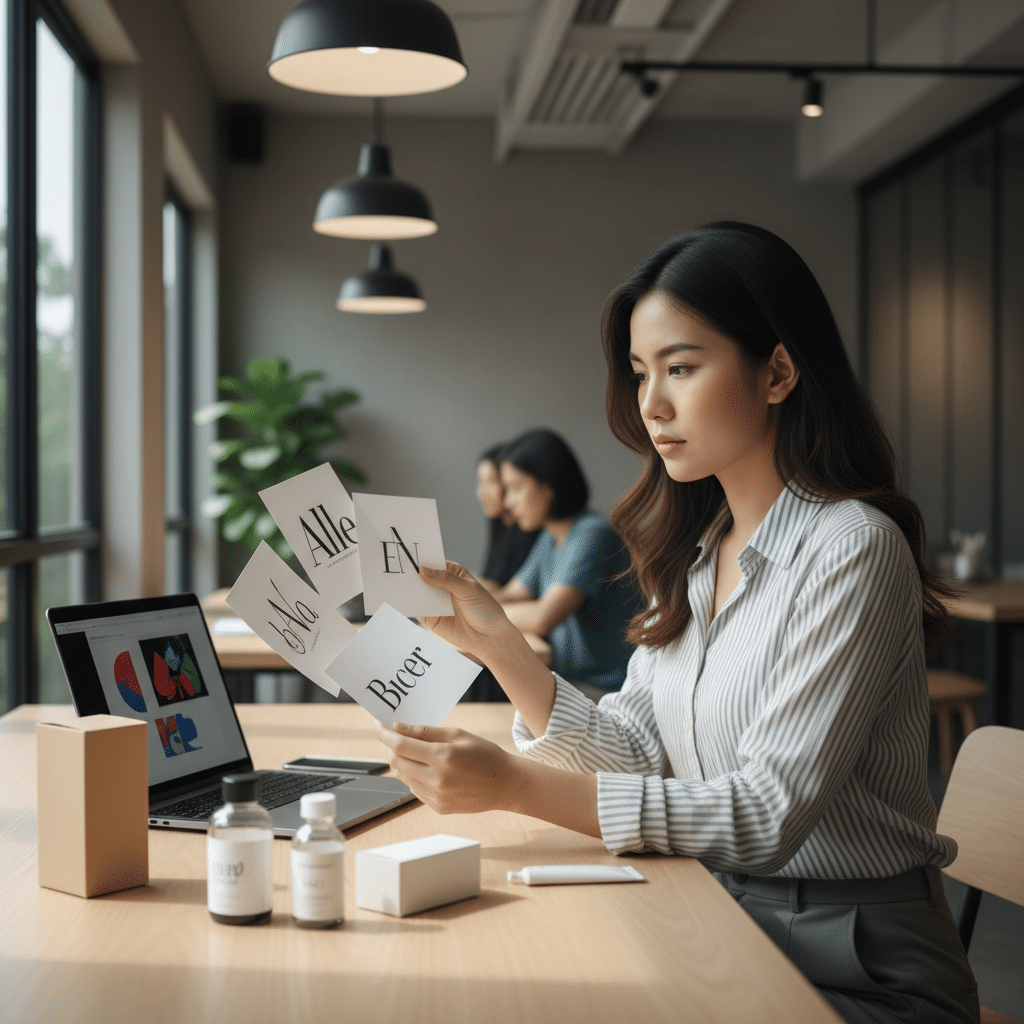
เลือกฟอนต์ผิด ชีวิตเปลี่ยน! จิตวิทยาฟอนต์สร้างแบรนด์ SME
การตัดสินใจว่า เลือกฟอนต์ผิด ชีวิตเปลี่ยน! จิตวิทยาฟอนต์สร้างแบรนด์ SME อาจฟังดูเกินจริง แต่ในความเป็นจริงแล้ว การเลือกใช้ตัวอักษรหรือฟอนต์ (Font) เป็นมากกว่าแค่การตัดสินใจด้านการออกแบบ เพราะมันคือเครื่องมือสื่อสารทรงพลังที่ส่งผลโดยตรงต่อการรับรู้และความน่าเชื่อถือของแบรนด์ในสายตาผู้บริโภค การเลือกฟอนต์ที่ไม่เหมาะสมอาจบ่อนทำลายความไว้วางใจและสร้างความเสียหายต่อความภักดีของลูกค้า ทำให้การตัดสินใจที่ดูเหมือนเล็กน้อยนี้กลายเป็นปัจจัยเชิงกลยุทธ์ที่สำคัญอย่างยิ่งต่อความสำเร็จของแบรนด์
สรุปประเด็นสำคัญของการเลือกใช้ฟอนต์
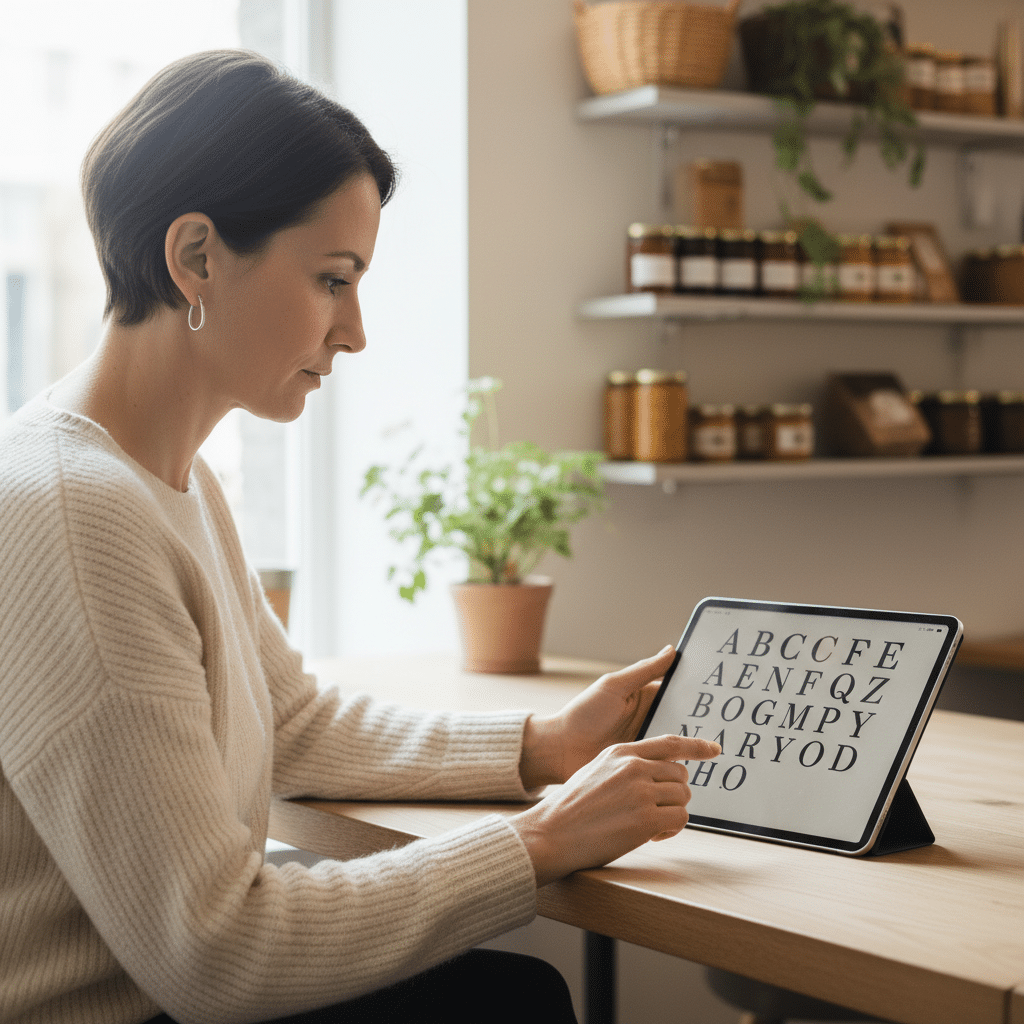
- การเลือกฟอนต์ส่งผลโดยตรงต่อการรับรู้: ฟอนต์ที่เหมาะสมสามารถเพิ่มการรับรู้ด้านนวัตกรรมได้ถึง 9% และสร้างความโดดเด่นให้แบรนด์ได้ 7%
- ฟอนต์สร้างความน่าเชื่อถือ: ฟอนต์ในกลุ่ม Geometric Sans-serif เช่น Gilroy Bold สามารถเพิ่มการรับรู้ถึงความน่าเชื่อถือและความเป็นของแท้ (Authenticity) ของแบรนด์ได้ถึง 5%
- ประเภทฟอนต์สื่อสารบุคลิกที่แตกต่าง: ฟอนต์กลุ่ม Serif (มีเชิง) สื่อถึงคุณภาพ ความหรูหรา และความน่าจดจำ ในขณะที่ฟอนต์กลุ่ม Sans-serif (ไม่มีเชิง) สื่อถึงความสำเร็จ ความจริงใจ และความทันสมัย
- ฟอนต์คืออัตลักษณ์ของแบรนด์: การเลือกฟอนต์เปรียบเสมือนการเลือกเครื่องแต่งกายให้กับแบรนด์ เป็นองค์ประกอบพื้นฐานที่กำหนดทิศทางการรับรู้ทั้งหมดของลูกค้าที่มีต่อแบรนด์
- ความผิดพลาดมีราคาสูง: สินค้าคุณภาพสูงที่ใช้ฟอนต์ไม่เหมาะสมอาจถูกมองว่าไม่น่าเชื่อถือ ในขณะที่แบรนด์สมัยใหม่ที่ใช้ฟอนต์ไม่เข้ากันอาจดูตกยุค ซึ่งส่งผลกระทบต่อยอดขายโดยตรง
จิตวิทยาฟอนต์คืออะไร และสำคัญต่อ SME อย่างไร
จิตวิทยาฟอนต์ (Font Psychology) คือการศึกษาว่ารูปแบบตัวอักษรที่แตกต่างกันส่งผลต่อความคิด ความรู้สึก และพฤติกรรมของมนุษย์อย่างไร ในบริบทของการสร้างแบรนด์สำหรับธุรกิจขนาดกลางและขนาดย่อม (SME) เรื่องนี้มีความสำคัญอย่างยิ่ง เพราะฟอนต์คือองค์ประกอบแรกๆ ที่ลูกค้าสัมผัสผ่านโลโก้ บรรจุภัณฑ์ เว็บไซต์ หรือสื่อส่งเสริมการขายต่างๆ มันทำหน้าที่เป็น “ภาษากาย” ของแบรนด์ สื่อสารบุคลิกภาพและคุณค่าออกไปก่อนที่ลูกค้าจะได้อ่านข้อความเสียอีก
สำหรับเจ้าของธุรกิจ SME ที่มีทรัพยากรจำกัด การทำความเข้าใจในเรื่องนี้ถือเป็นความได้เปรียบในการแข่งขัน การเลือกฟอนต์ที่ถูกต้องตั้งแต่เริ่มต้นสามารถสร้างความไว้วางใจ สร้างความแตกต่างจากคู่แข่ง และดึงดูดกลุ่มเป้าหมายที่ใช่ได้โดยไม่ต้องใช้งบประมาณมหาศาล ในทางกลับกัน การมองข้ามความสำคัญของฟอนต์อาจทำให้การลงทุนด้านการตลาดอื่นๆ ไม่เกิดประสิทธิภาพเท่าที่ควร เพราะภาพลักษณ์ของแบรนด์ขาดความน่าเชื่อถือหรือไม่สอดคล้องกัน
พลังของฟอนต์ที่ส่งผลต่อการรับรู้แบรนด์
พลังของตัวอักษรนั้นมีผลกระทบที่สามารถวัดผลได้ต่อการที่ผู้บริโภคจะมองแบรนด์ของคุณอย่างไร ฟอนต์ที่ปรากฏบนโลโก้ ฉลากสินค้า หรือสื่อการตลาดต่างๆ เป็นตัวกำหนดการรับรู้ของลูกค้าในหลายมิติ ตั้งแต่ความน่าเชื่อถือไปจนถึงความทันสมัย
สร้างความน่าเชื่อถือและความโดดเด่น
ลองจินตนาการถึงธนาคารหรือสถาบันการเงินที่ใช้ฟอนต์ลายมือแบบเด็กๆ บนหน้าเว็บไซต์ หรือแบรนด์สินค้าแฟชั่นสุดหรูที่ใช้ฟอนต์หนาเทอะทะบนป้ายราคา ความรู้สึกขัดแย้งที่เกิดขึ้นนี้สามารถทำลายความไว้วางใจของลูกค้าได้ในทันที สินค้าที่มีคุณภาพยอดเยี่ยมอาจถูกมองว่าไม่น่าเชื่อถือหากจับคู่กับฟอนต์ที่ดูราคาถูกหรือไม่เป็นมืออาชีพ ในขณะเดียวกัน แบรนด์ที่ต้องการสื่อสารถึงความทันสมัยและนวัตกรรมอาจดูตกยุคไปถนัดตาหากเลือกใช้ฟอนต์ที่ไม่สอดคล้องกัน สิ่งเหล่านี้ส่งผลโดยตรงต่อการตัดสินใจซื้อและความภักดีของลูกค้าในระยะยาว
ตัวอย่างผลกระทบจากงานวิจัย
ข้อมูลจากการวิจัยแสดงให้เห็นถึงผลกระทบที่เป็นรูปธรรมของการเลือกใช้ฟอนต์:
- การรับรู้ด้านนวัตกรรม (Perceived Innovation): การเลือกฟอนต์ที่เหมาะสมสามารถเพิ่มการรับรู้ว่าแบรนด์มีความเป็นนวัตกรรมได้ถึง 9%
- ความโดดเด่นของแบรนด์ (Brand Distinctiveness): ฟอนต์ที่ใช่ช่วยเสริมสร้างความแตกต่างและทำให้แบรนด์โดดเด่นจากคู่แข่งได้มากขึ้น 7%
- ความน่าเชื่อถือและความเป็นของแท้ (Authenticity): ฟอนต์ประเภท Geometric Sans-serif ที่ได้รับความนิยมทั่วโลกอย่าง Gilroy Bold ได้รับการพิสูจน์แล้วว่าสามารถเพิ่มการรับรู้ถึงความเป็นของแท้และความน่าเชื่อถือของแบรนด์ในสายตาผู้บริโภคได้ถึง 5%
การเลือกฟอนต์ไม่ใช่แค่เรื่องของความสวยงาม แต่เป็นกลยุทธ์สำคัญในการสร้างแบรนด์ที่ประสบความสำเร็จ ซึ่งลูกค้าสามารถจดจำและไว้วางใจได้ในทันที
เจาะลึกประเภทฟอนต์และผลกระทบทางจิตวิทยา
ฟอนต์สามารถแบ่งออกเป็นหลายประเภท แต่ละประเภทมีความสามารถในการสื่อสารคุณสมบัติและบุคลิกของแบรนด์ที่แตกต่างกัน การทำความเข้าใจลักษณะเด่นของฟอนต์แต่ละกลุ่มจะช่วยให้ผู้ประกอบการ SME สามารถเลือกเครื่องมือที่เหมาะสมที่สุดในการสื่อสารกับลูกค้าได้
ฟอนต์มีเชิง (Serif): ความคลาสสิกที่น่าเชื่อถือ
ฟอนต์ประเภท Serif คือฟอนต์ที่มี “เชิง” หรือขีดเล็กๆ ที่ปลายของตัวอักษร เช่น Times New Roman, Garamond หรือ Cotford ฟอนต์กลุ่มนี้มีประวัติศาสตร์ยาวนานและมักถูกใช้ในสื่อสิ่งพิมพ์ที่เป็นทางการ เช่น หนังสือ หนังสือพิมพ์ หรือเอกสารทางวิชาการ ด้วยเหตุนี้ ฟอนต์ Serif จึงมักสื่อถึงความรู้สึกดังต่อไปนี้:
- คุณภาพสูง (High Quality): ให้ความรู้สึกของงานที่ประณีต มีระดับ และน่าเชื่อถือ
- น่าจดจำ (Memorable): โครงสร้างที่เป็นเอกลักษณ์ช่วยให้จดจำได้ง่าย
- น่าเชื่อถือ (Trustworthy): สื่อถึงความมั่นคง ประสบการณ์ และความเป็นทางการ
- ความหรูหรา (Luxury): มีความเชื่อมโยงอย่างยิ่งกับแบรนด์แฟชั่น สินค้าฟุ่มเฟือย และบริการระดับพรีเมียม
เหมาะสำหรับ: ธุรกิจที่ต้องการสร้างภาพลักษณ์ที่น่าเชื่อถือ เป็นทางการ มีประวัติศาสตร์ยาวนาน หรือแบรนด์ที่เกี่ยวข้องกับสินค้าหรูหรา เช่น สำนักงานกฎหมาย, ที่ปรึกษาทางการเงิน, แบรนด์นาฬิกา, หรือโรงแรมระดับ 5 ดาว